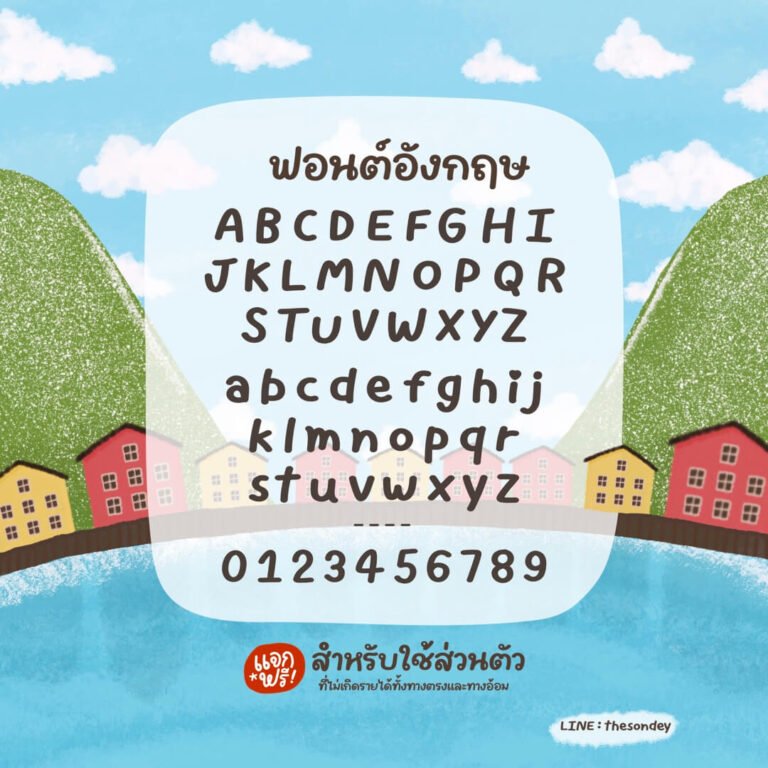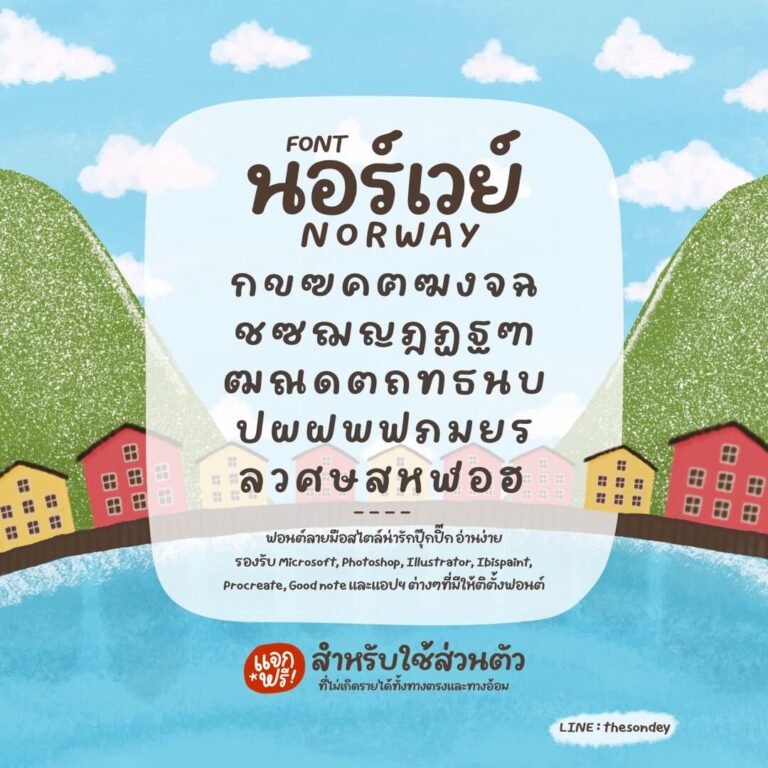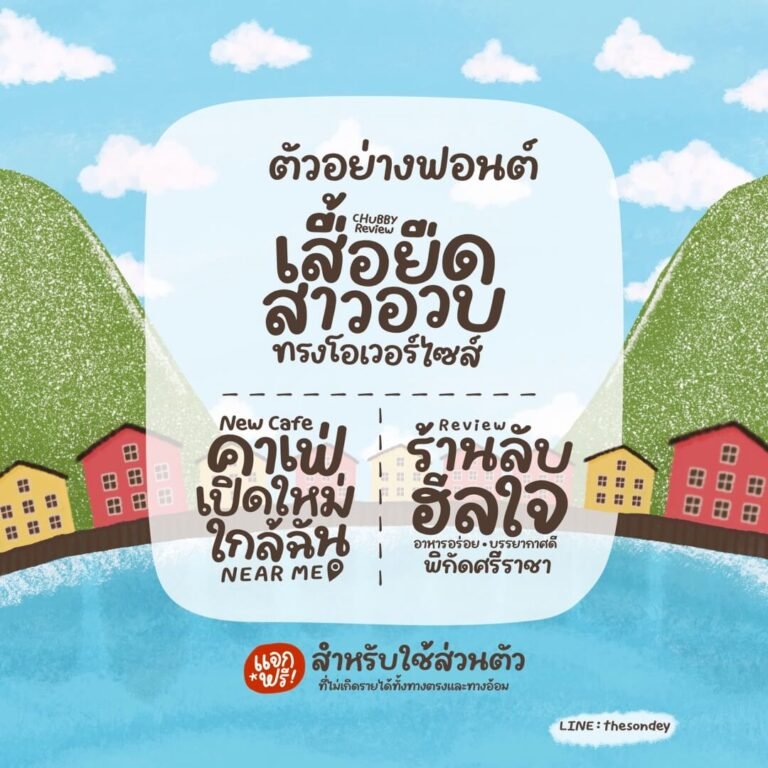
นอร์เวย์ (PG Norway)
ฟอนต์ลายมือสไตล์น่ารักปุ๊กปิ๊ก อ่านง่าย รองรับ Microsoft, Photoshop, Illustrator, CapCut, ibisPaint, Procreate, Good Note และแอปฯ ต่างๆ ที่มีให้ติดตั้งฟอนต์